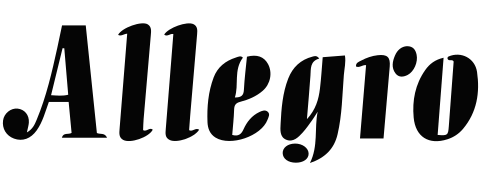
| カテゴリ | ディスプレイ セリフ ディドン |
| デザイナー | ハンス・ボーン |
| 鋳造所 | ルートヴィヒ&マイヤー |
アレグロはディスプレイ用に設計されたセリフ 書体である。フランクフルトのルートヴィヒ・アンド・マイヤー活字鋳造所のためにハンス・ボーンがデザインし、1936年に発売された。[1] [2]
アレグロは、19 世紀初頭頃からの、極太のストロークと極細のストロークを交互に強調したディドーネスタイルにインスピレーションを得ています。ただし、通常は細いストロークが使用される文字の部分を中断することで、ステンシルレタリングに似た効果を生み出し、わずかな傾斜が手書きを、ボール ターミナルとスワッシュが音楽を連想させます。アレグロは、特に本の表紙などの装飾目的で使用されます。
Allegro はデジタル化されており、Bitstreamによって販売されています。Allegro の説明には、次のブレンドについて書かれています。